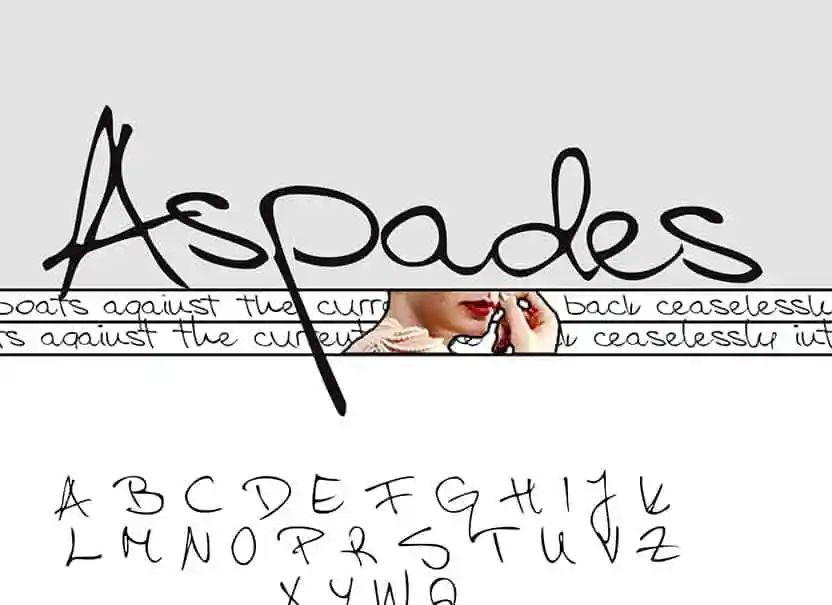
Aspades Handwritten Font
Bem-vindo ao mundo das fontes! Nesta categoria especial dedicada a Script Fonts está Aspades Handwritten Font, criado por Hamilton. Aspades é uma elegante escrita à mão com um ar moderno e versátil. Este tipo de letra é perfeita para múltiplas aplicações, como slogans, cabeçalhos de blog, posters, casamentos, marcações, logotipos, moda, roupas, cartões personalizados, convites e até mesmo a embalagem de papelaria. Aspades Handwritten Font é uma ótima escolha para quem busca um toque delicado e único em seus projetos gráficos. Tente ela agora em seu próximo projeto!